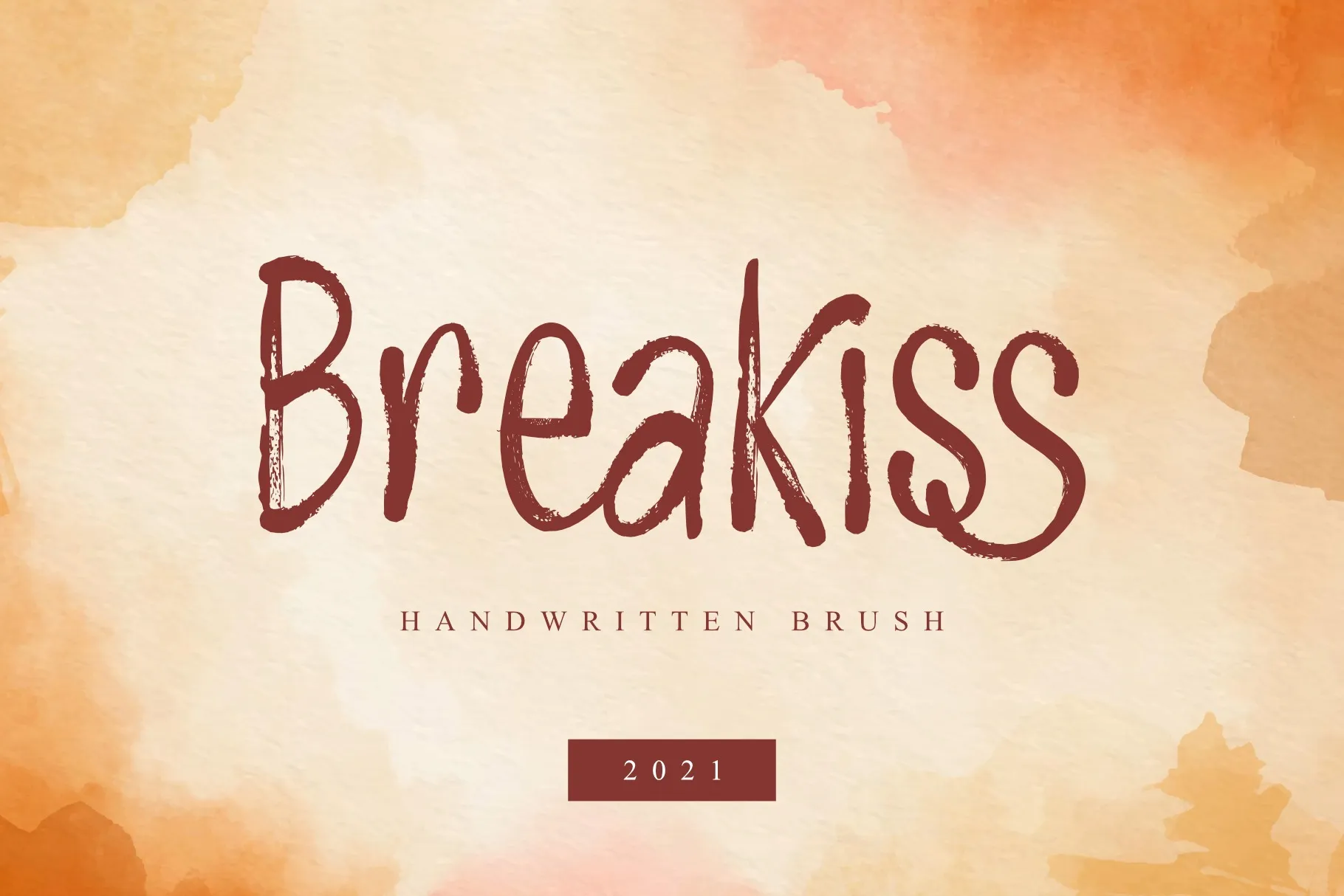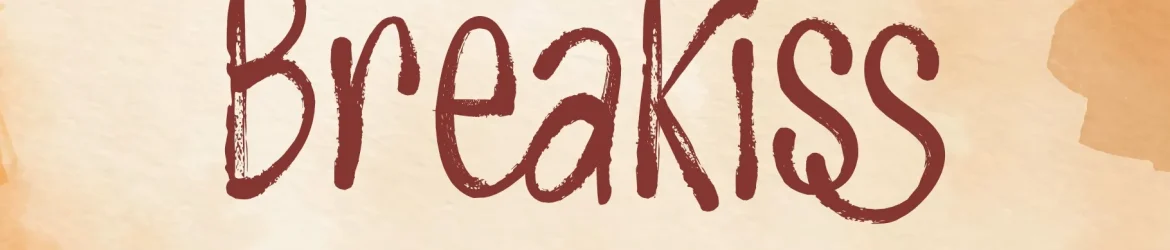
Breakiss Font – Download Grátis
A Breakiss Font é uma deliciosa combinação de escrita a mão e textura de borracha seca que cria um visual único e envolvente. Essa fonte é perfeitamente projetada para designers de arte que desejam criar designs originais, especialmente aqueles que gostam de fazer designs de crafts. Com sua textura ressecada e detalhes duros, ela permite uma expressão única em qualquer tipo de design, seja ele para redes sociais, marcação, publicidade, embalagens de produtos, etiquetas, materiais de merchandising ou até mesmo postais. A Breakiss é a escolha perfeita para transformar suas criações digitais em algo ainda mais especial e único. Experimente essa fonte moderna e elegante que vai tornar seus projetos imbatíveis.